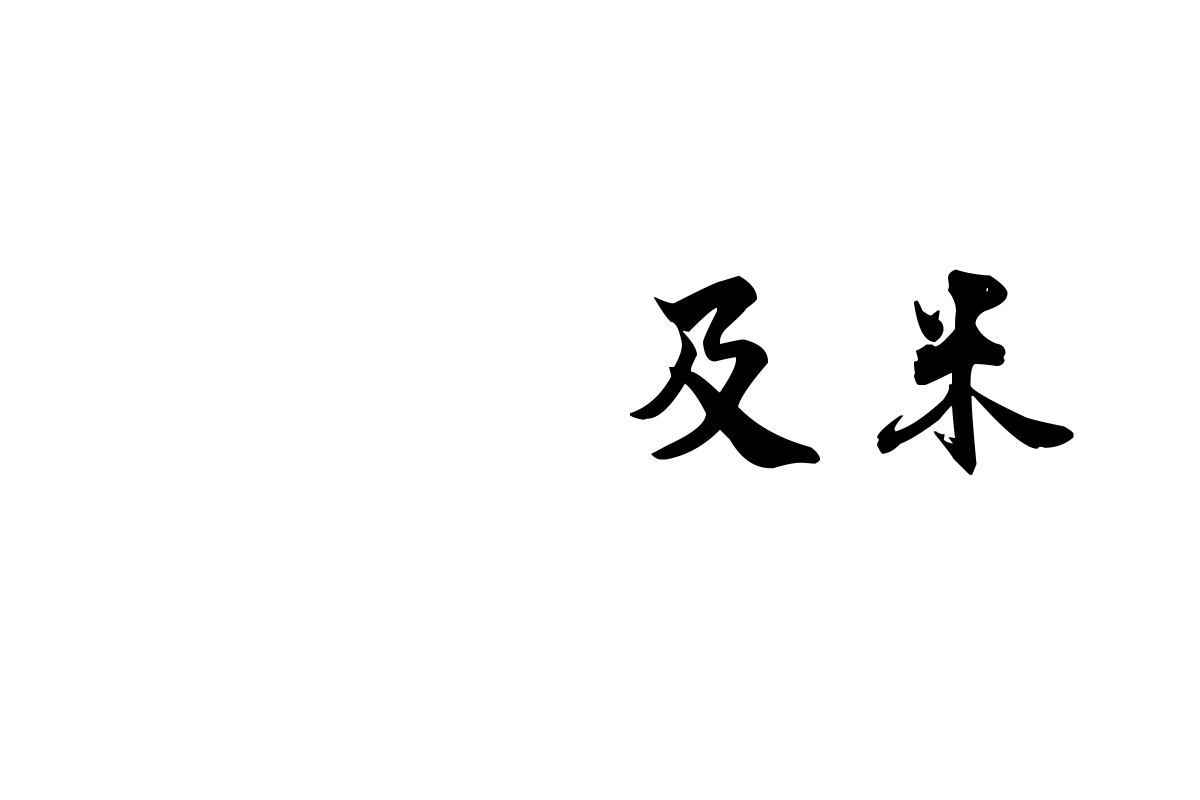
汉呈王天喜任我行字体是一种具有独特风格的中文字体,它的特点是字形圆润饱满,线条流畅自然。这种字体适合用于标题、广告、宣传等场合,能够给人留下深刻的印象。
汉呈王天喜任我行字体的笔画粗细适中,既有力度又不失柔和,给人一种舒适的感觉。同时,这种字体的字形结构紧凑,但不失灵动,使得整体看起来既庄重又富有活力。
此外,汉呈王天喜任我行字体还具有一定的艺术感,它的线条变化丰富多样,既有直线也有曲线,既有粗线也有细线,使得整个字体更加生动有趣。
总的来说,汉呈王天喜任我行字体是一种非常适合现代设计需求的中文字体,无论是在商业还是文化领域都有着广泛的应用前景。